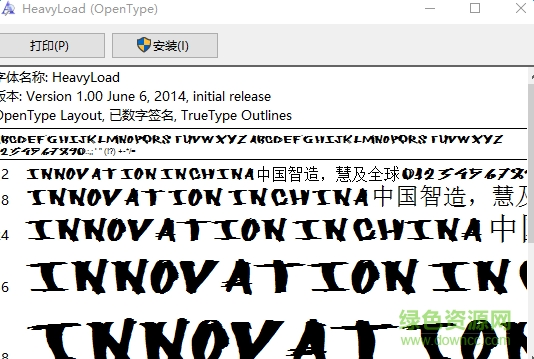
HeavyLoad
HeavyLoad字體是一款很有特色的英文字體,而且這款字體有著強烈的藝術(shù)感,比較適合用于藝術(shù)設(shè)計、廣告設(shè)計等方面,如果大家需要這款字體的話可以隨時來綠色資源網(wǎng)下載。
HeavyLoad字體是一款很不錯的電腦英文字體,寫出來的字很美觀、大全,具有藝術(shù)風(fēng)格,喜歡的朋友就快來綠色資源網(wǎng)下載吧。